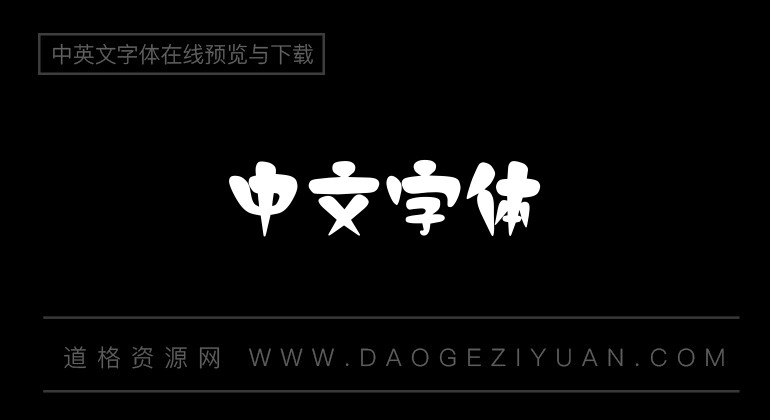
迷你简萝卜
? 迷你简萝卜是一款简约时尚的字体,它采用现代化的技术,拥有精致的线条和更多的字形,以及更多的中文字体,使其成为一款极具艺术性的字体。它既可以用于印刷,也可以用于网络和移动应用,为您提供更多的设计空间。
迷你简萝卜是一款非常不错的手写艺术字体,具有很好的视觉感,适合于文化类的宣传设计、商业类品牌的广告和产品包装设计以及个性化文字排版等较多场景。